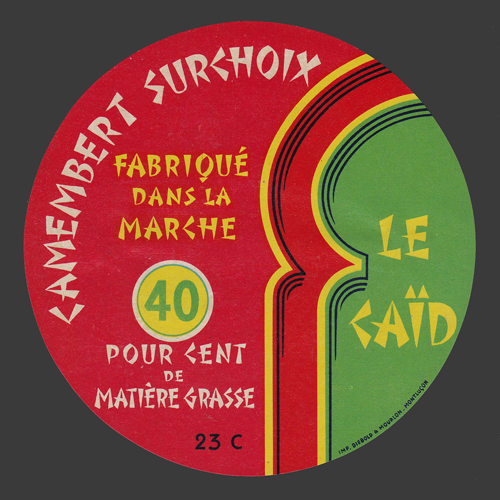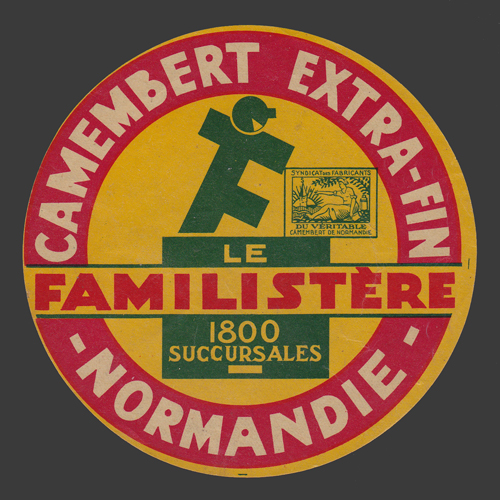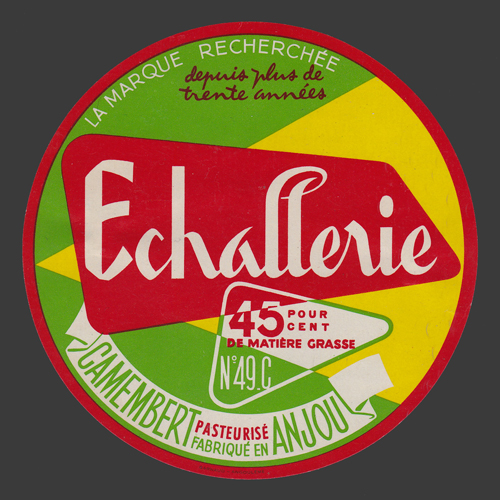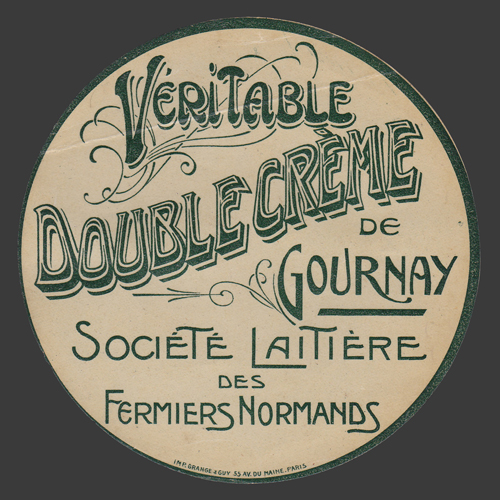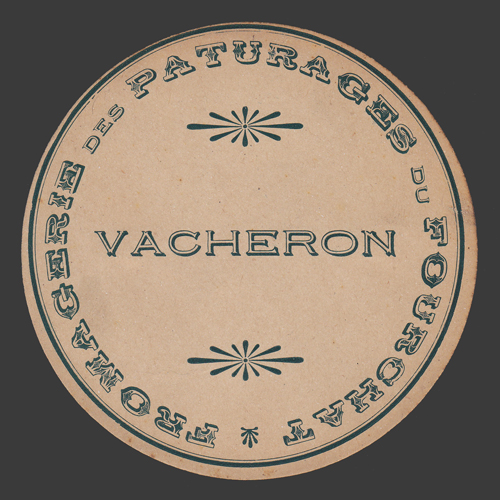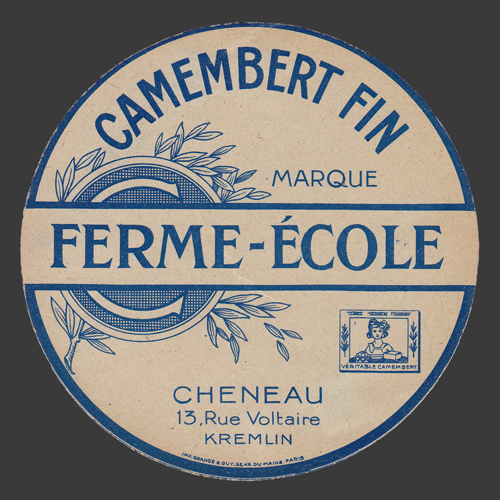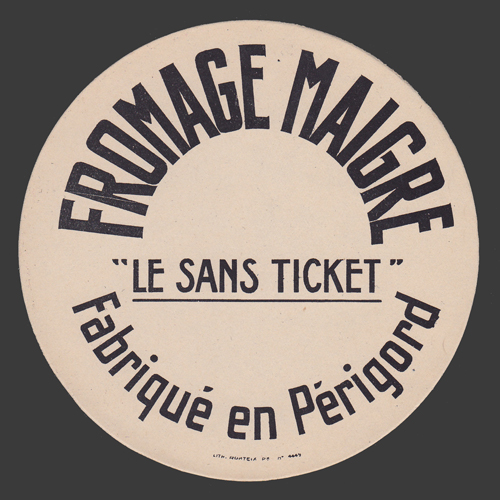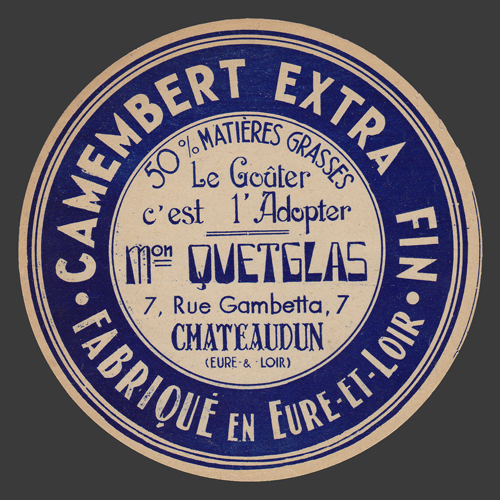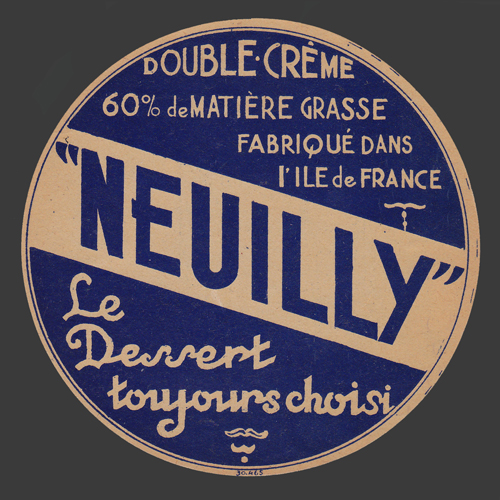
Etiquettes et Typographie.
ÉTIQUETTES ET TYPOGRAPHIE
S'il est un thème négligé par les collectionneurs d'étiquettes, c'est bien celui qui ne comporte aucune image, le texte seul faisant office d'illustration. Parent pauvre de la collection, dans tous les sens du terme, pauvre dans sa conception, pauvre dans son apparence, souvent pauvre dans sa fabrication. Cependant, ces étiquettes témoignent elles aussi à leur façon de leur époque. La typographie accompagne et souligne les styles et les modes. Elle en exprime toutes les facettes au même titre qu'une illustration élaborée. Ces étiquettes dont seule la typographie est présente, agrémentées parfois de quelques fantaisies graphiques ont été conçues soit volontairement humbles et modeste pour communiquer une simplicité voulue ou par défaut de moyens ou par manque de volonté. L'étiquette "Le sans ticket" par exemple participe de ces principes alors que les étiquettes réalisées par Henri Pennec sont conçues en quelque sorte comme de véritables anti-étiquettes. D'autres imprimées en bichromie, le plus souvent blanc/bleu, sont destinées aux fromages double crème, frais ou de régime. Mais beaucoup assument le choix de la typographie avec un graphisme affirmé, devrais-je dire de "caractère".
Comme tout, la typographie a évolué à travers les âges, en fonction des goûts et des usages, bien sûr, mais aussi en fonction des techniques dont elle est tributaire. Nombre de typographes se sont évertués, pour en faciliter l'usage, à en établir un classement ; parmi eux Francis Thibaudeau avait défini en 1921 quatre grandes familles chacune déterminée par le type d'empâtement des lettres. La forme de ceux-ci répondant à l'évolution des différentes techniques utilisées pour les dessiner, les graver ou les imprimer. C'est, de toutes les classifications, la plus aisée à appréhender si l'on n'est pas spécialiste.
La première de ces familles se nomme "les Antiques" (ou bâton) ; caractère sans empâtement, (lettres dessinées avec le doigt sur le sable par exemple). Deuxième famille "les Elzévir", du nom d'une célèbre famille de typographes hollandais, regroupe les caractères à empâtements triangulaires (comme ceux des lettres gravées dans la pierre dont la base des empâtements est finalisée et accentuée par deux coups de burin). Troisième famille "les Didot" du nom du célèbre imprimeur Firmin Didot ; ils définissent les caractères dont les empâtements sont faits d'un trait fin de tire-ligne (technique qui n'a pu apparaître qu'avec l'invention de la lithographie). Enfin la famille des "Egyptiennes" qui regroupe les caractères à empâtement rectangulaire (cette famille de caractères a fait son apparition avec les besoins de la presse et de l'affichage à la recherche de caractères forts et puissants).
À ces quatre grandes familles il faut ajouter les cursives ou scriptes (toutes lettres issues de l'écriture manuelle), les Gothiques (origine France) ou les Frakturs (origine Allemande), enfin les fantaisies (lettres ne respectant aucune règle et obéissant uniquement à l'imagination de son créateur). À cette classification Thibaudeau s'est ajoutée en 1954 celle du typographe Maximillien Vox qui, lui, décomposa les caractères en neuf familles, dites "fondamentales", familles qu'il serait fastidieux de détailler ici. Ayons par contre présent à l'esprit que la photocomposition, les déformations et modifications d'approche que nous permettent les ordinateurs ont considérablement bousculé ce qui semblait figé. Le déferlement incessant de caractères mixtes ou fantaisistes venus des créateurs du monde entier dans lesquels le besoin de se différencier l'emporte le plus souvent sur le souci d'une lecture aisée.
Mais arrêtons nous un instant sur les bouleversements engendrés par l'arrivée des nouvelles techniques de reproduction (photocomposition, numérisation…). La plupart des caractères existants et notamment les plus anciens n'étant pas protégés (comme certains de nos fromages) furent copiés, déformés, trahis, quelquefois débaptisés. C'est ainsi par exemple que le Garamond (gravé au 16e siècle par Claude Garamont) caractère magnifique, aboutissement d'une longue expérience, dessiné exclusivement en italique et en romain (caractère droit) se retrouve aujourd'hui comme beaucoup d'autres, interprété et déformé selon la fantaisie d'intervenants ineptes, dans des graisses et des contorsions qui le rendent méconnaissable. Avez-vous remarqué l'inconfort que l'on éprouve à utiliser les couverts "modernes" dans beaucoup de restaurants alors que les couverts dits des "Fermiers Généraux" avaient atteint une parfaite ergonomie dès la fin du 18e siècle.
La typographie c'est tout d'abord un dessin particulier de la lettre dont les fonctions sont bien définies. À l'origine sont les caractères de labeur destinés à l'édition (livres, journaux) ou aux "travaux de ville" (cartes de visite, têtes de lettres). Ces caractères employés essentiellement dans de petits corps doivent être d'une grande facilité de lecture et en cela ils sont, restent et resteront à l'écart des modes. Un exemple parfait de ces caractères est le Times New Roman, aujourd'hui fort répandu ; il fut créé et gravé de 1930 à 1932. Le journal éponyme (dont je ne sais s'il en fut le commanditaire) fut dans sa nouvelle maquette entièrement composé de ce nouveau caractère. Afin d'en faire la promotion, le numéro 51634 du "Times" daté du 8 mars 1950 qui rendait compte de la visite du président Vincent Auriol à la Cour d'Angleterre fut réimprimé en fac-similé sur papier Bible au format incroyable de 13 cm sur 18 cm. Chaque lettre restant distinctement identifiable. L'incontestable démonstration de la lisibilité de ces exemplaires destinés aux professionnels en assura la promotion.
En dehors des caractères de labeur, se trouvent les caractères destinés aux titres, aux enseignes, à l'affichage dont les contraintes sont moindres dans la mesure où leur emploi ne dépasse pas la plupart du temps la longueur d'une petite phrase, le plus souvent quelques mots. Là, l'originalité, la créativité, la fantaisie peuvent s'exprimer pleinement, mais n'oublions pas que tout l'art du typographe consiste à adapter au mieux la forme au sens. On n'écrit pas "béton" comme on écrit "dentelle", et la pochette de disque d'un rocker ne doit pas se confondre avec l'étiquette d'une crème apaisante. Le grand typographe sera celui qui tout en appliquant ces règles élémentaires y ajoutera sa patte, sa personnalité.
Il semblerait que la typographie soit perçue comme un univers austère ; je voudrais lever ce préjugé en évoquant une plaisanterie que j'oserais qualifier d'éculée : - élève à l'école Estienne à Paris le dessin d'alphabets faisant partie des prémices de notre enseignement, le professeur en nous corrigeant ne manquait pas à l'occasion de nous faire remarquer avec malice que notre P était trop près de notre Q et qu'il fallait y mettre un peu d'air. À la section composition typographique, il était de bon ton de signaler que si on voulait faire une bonne impression il fallait avoir un bon caractère.
J'en termine là des digressions qui nous éloignent de notre sujet : étiquettes et typographie. En espérant que ces quelques informations transmises vous permettront de jeter désormais un œil bienveillant sur ces humbles et discrètes étiquettes.